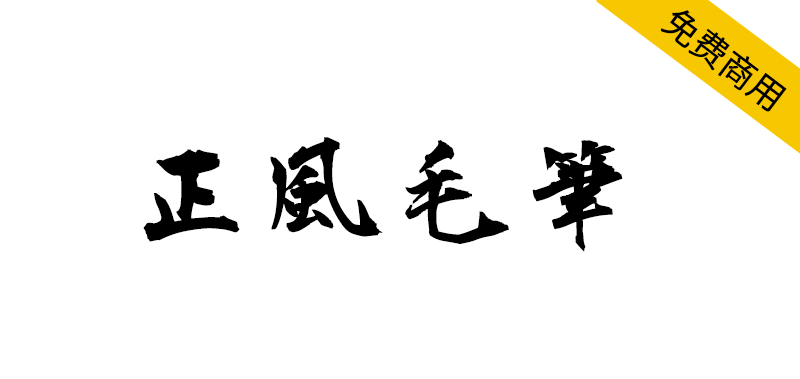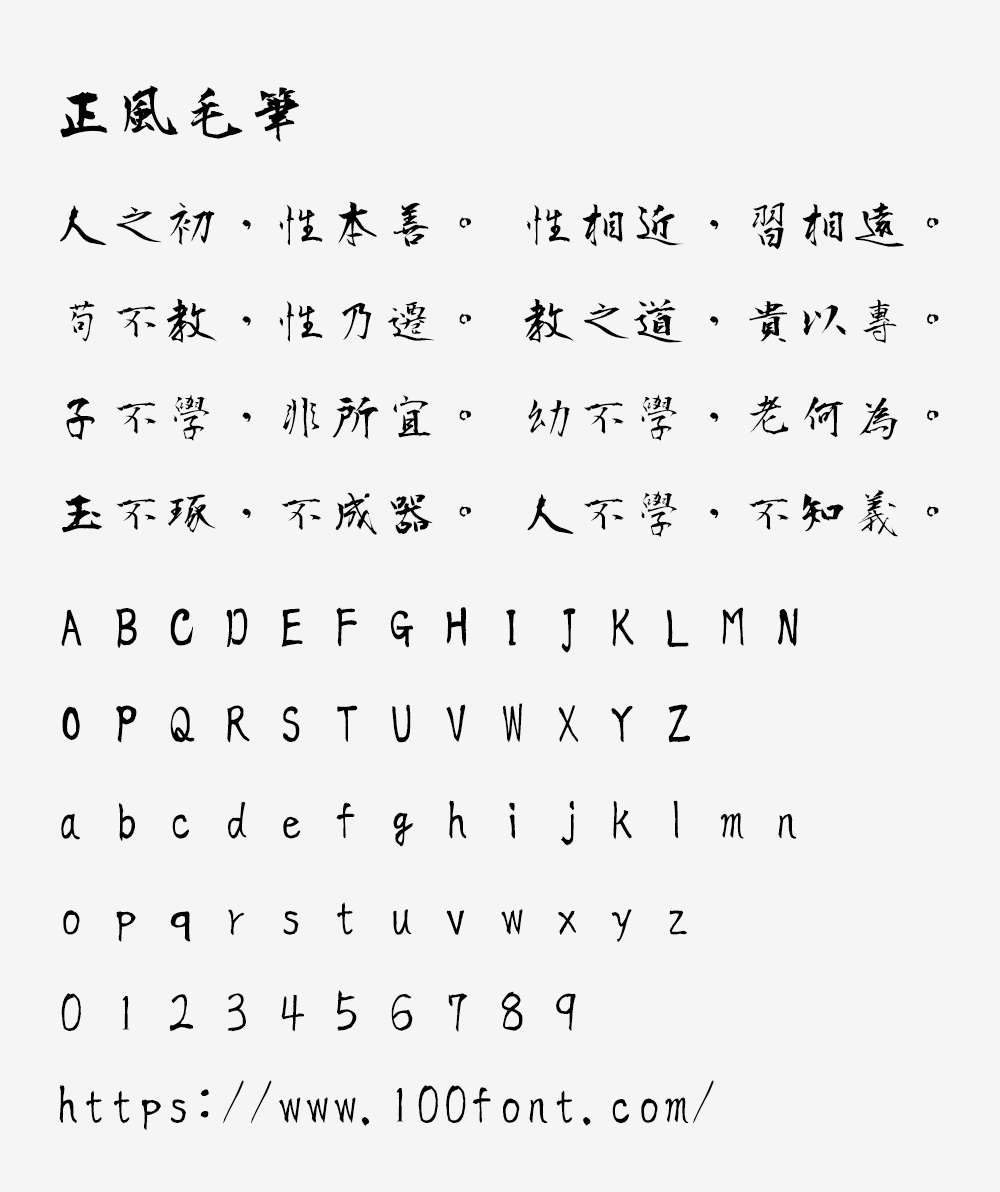
正风毛笔字体是基于衡山毛笔字体行书的开放原始码中文字型。衡山毛笔行书字体是来自于日本书法家青柳衡山,修改前文字+符号数:7582字,修改后文字+符号数:23699字。欢迎大家自由应用、自由改作!
字体特色:弥补繁体中文常用字缺字缺憾,调整为5种字重,清除衡山毛笔行书字体里空白的文字,标点符号位置调整为台湾常见的置中用法,增加部分台湾口语、闽南语和客语中文字。